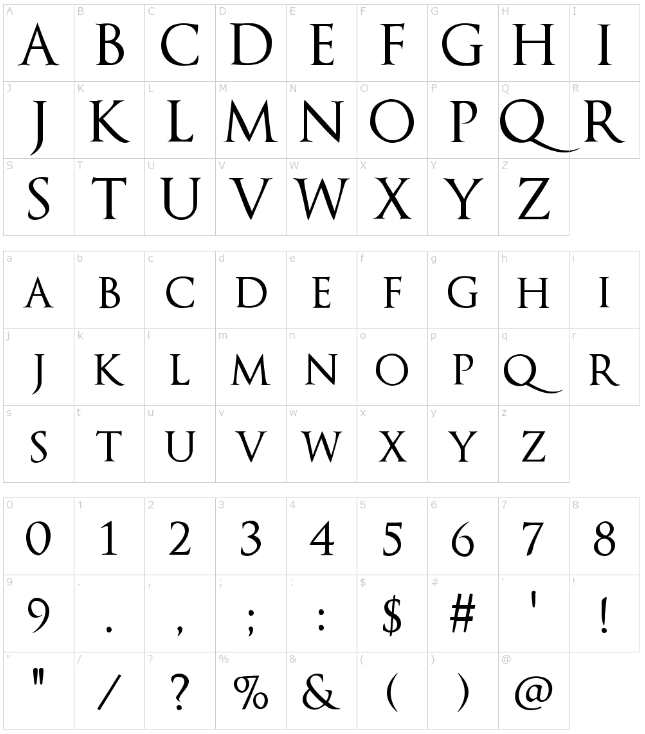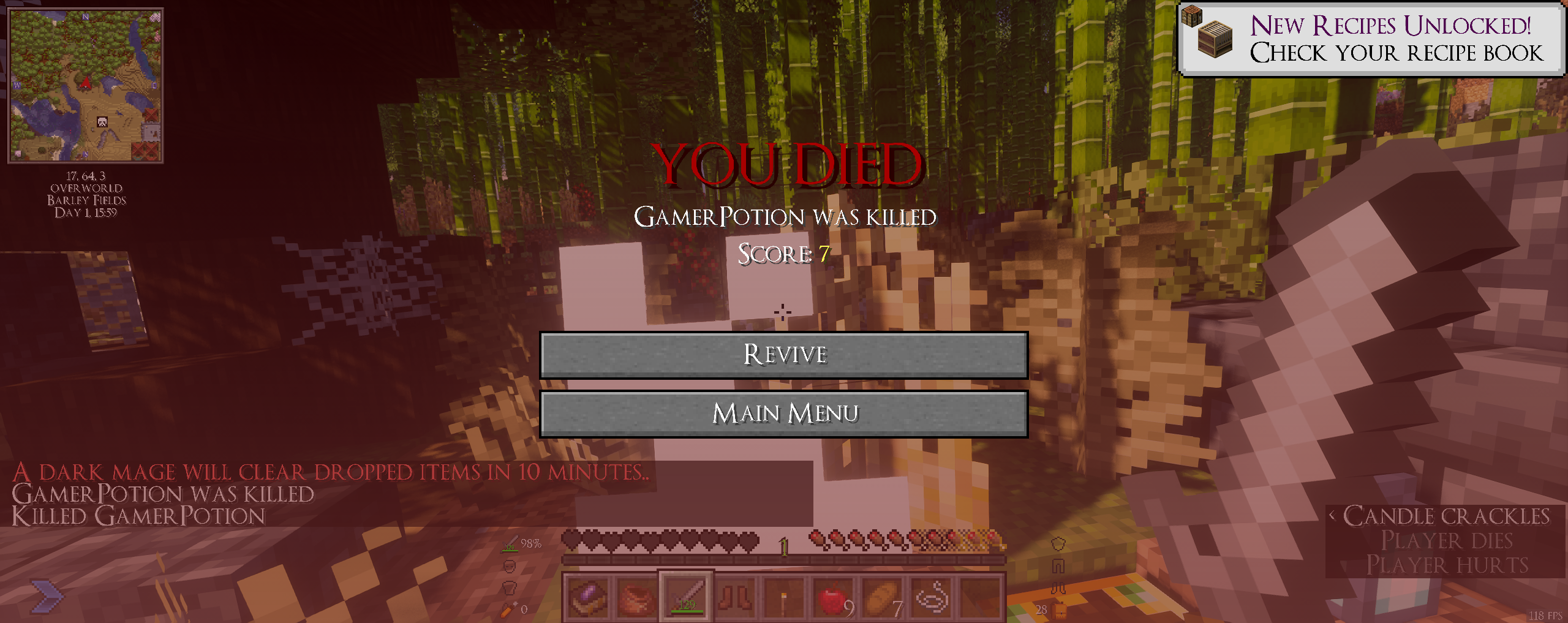
Souls Font для Minecraft: Готический шрифт в стиле Dark Souls
Если вы хотите добавить в Minecraft атмосферу мрачного фэнтези, как в Dark Souls, то Souls Font — идеальное решение. Этот готический шрифт придаст вашему игровому интерфейсу средневековый стиль, сохраняя при этом читаемость.
🔥 Что такое Souls Font?
Souls Font — это пользовательский шрифт для Minecraft, вдохновленный культовой серией Dark Souls. Он создан для модпака DarkRPG, но теперь доступен всем игрокам.
Особенности:
✔ Готический и средневековый дизайн
✔ Улучшенная читаемость по сравнению с другими стилизованными шрифтами
✔ Основан на Optimus Princeps Font от Manfred Klein
🖼️ Как выглядит Souls Font в игре?
Шрифт отлично сочетается с модами в духе Dark Souls, такими как:
- DarkRPG (для которого он изначально создавался)
- Epic Fight Mod
- Souls-Like Weaponry
Он придает тексту в чате, меню и интерфейсе атмосферу мрачного фэнтези, не жертвуя удобством чтения.
🏁 Заключение
Souls Font — отличный способ разнообразить визуальную составляющую Minecraft, добавив в неё нотки Dark Souls. Шрифт не только красивый, но и удобочитаемый, что делает его одним из лучших в своём роде.
Попробуйте его в связке с тематическими модами — и ваше приключение в кубическом мире станет ещё более захватывающим!